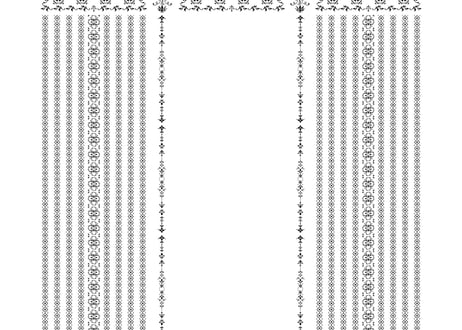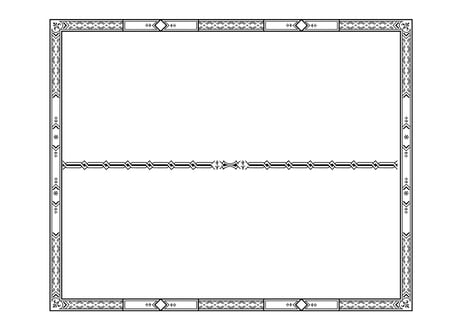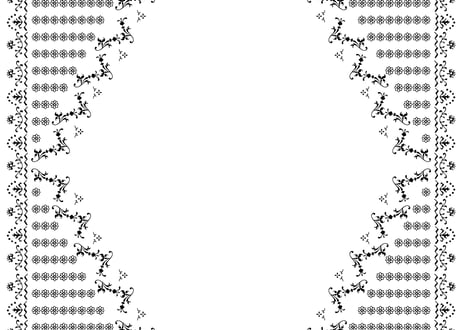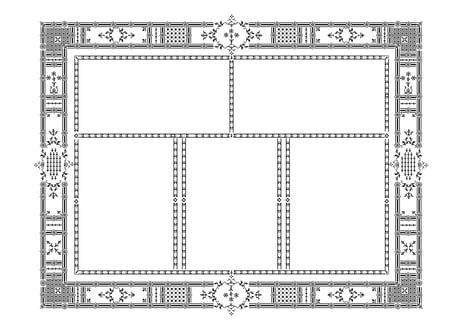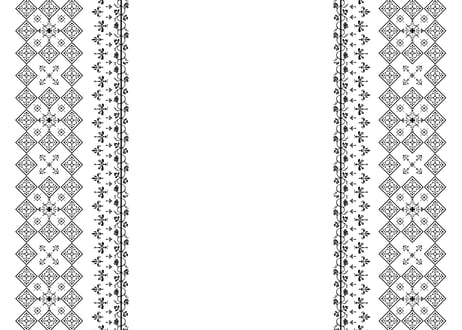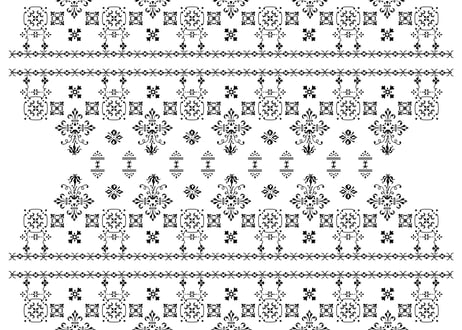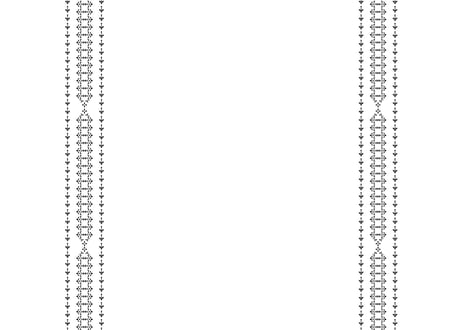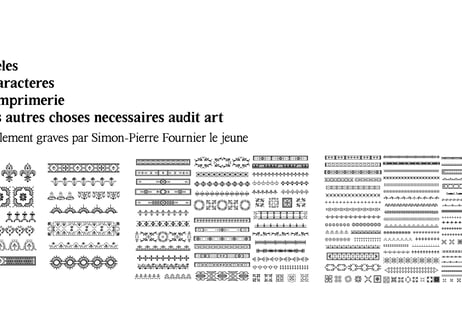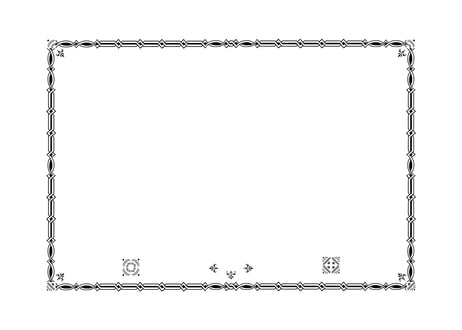
装飾活字:Modeles des caracteres de l'imprimerie et des autres choses necessaires audit art
1742年に発行された「Modeles des caracteres de l'imprimerie et des autres choses necessaires audit art / nouvellement gravés par Simon-Pierre Fournier le jeune」に収録された花形装飾活字をもとに、現代のデザイン環境で利用できるよう再構築したデータパッケージです。
資料に収録された装飾の形状や構成を可能な限り保持しながらデジタル化を行い、グラフィックデザイン、エディトリアルデザイン、ロゴ制作、パッケージデザインなど幅広い用途でご利用いただけます。
本プロジェクトは、フランスの美術大学図書館でデジタルアーカイブに携わる方とのご縁から始まりました。高解像度でスキャンされた原典資料をご提供いただき、そのデータをもとにAdobe Illustratorで一点ずつ丁寧にアウトライン化を行っています。
■元資料について
本商品は、18世紀フランスを代表する活字彫刻師 Simon-Pierre Fournier le Jeune による活字見本帳をもとに制作したアーカイブコレクションです。
活字だけでなく、花形装飾活字や印刷装飾の豊かなバリエーションが収録されており、当時の印刷文化やデザイン感覚を現代に伝える貴重な資料となっています。